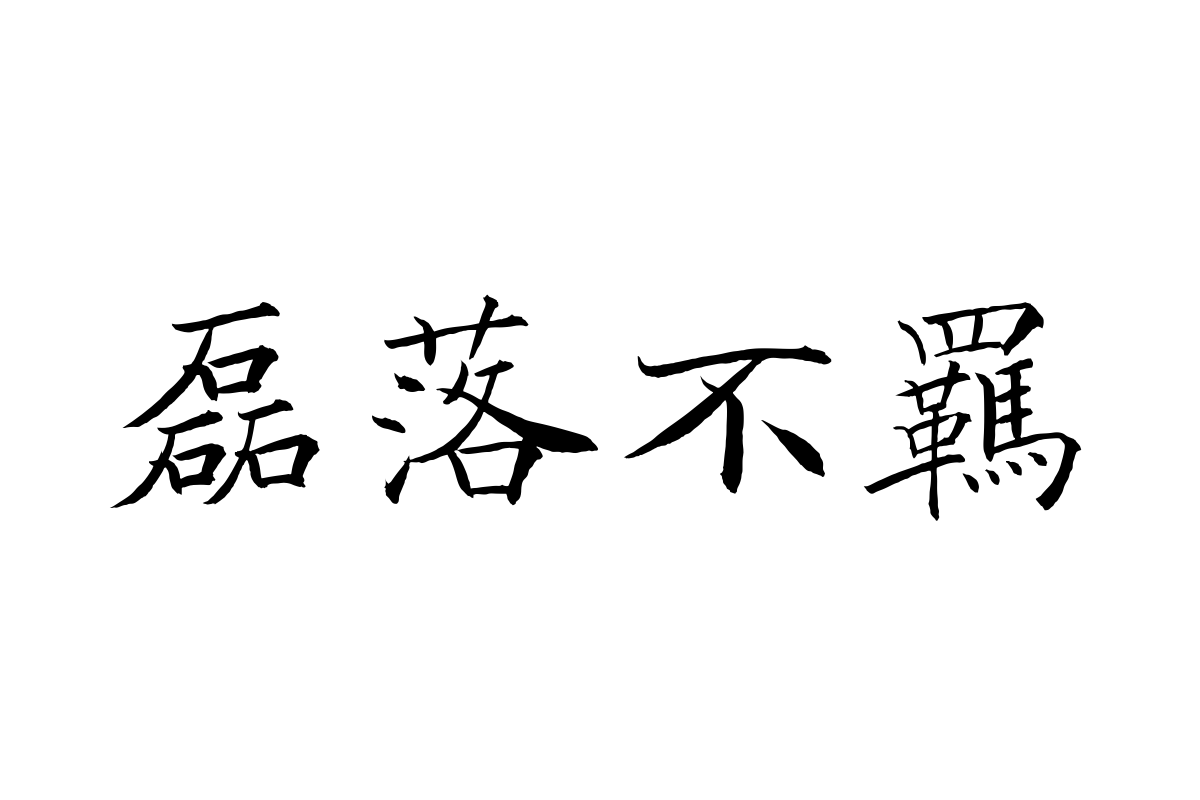
汉仪跃晰褚楷繁体是一款由汉仪公司推出的中文字体,具有独特的书法风格和艺术感。这款字体采用了褚楷为基础,结合了现代设计元素,使其更加符合现代人的审美需求。
汉仪跃晰褚楷繁体的特点如下:
1. 字形优美:该字体的字形线条流畅,笔画粗细适中,给人一种优雅、大气的感觉。
2. 风格独特:汉仪跃晰褚楷繁体在保持褚楷的基础上,融入了一些现代设计元素,使得字体更加时尚、前卫。
总之,汉仪跃晰褚楷繁体是一款具有独特风格的中文字体,适合用于各种印刷品和设计场景,能够满足现代人对审美的追求。